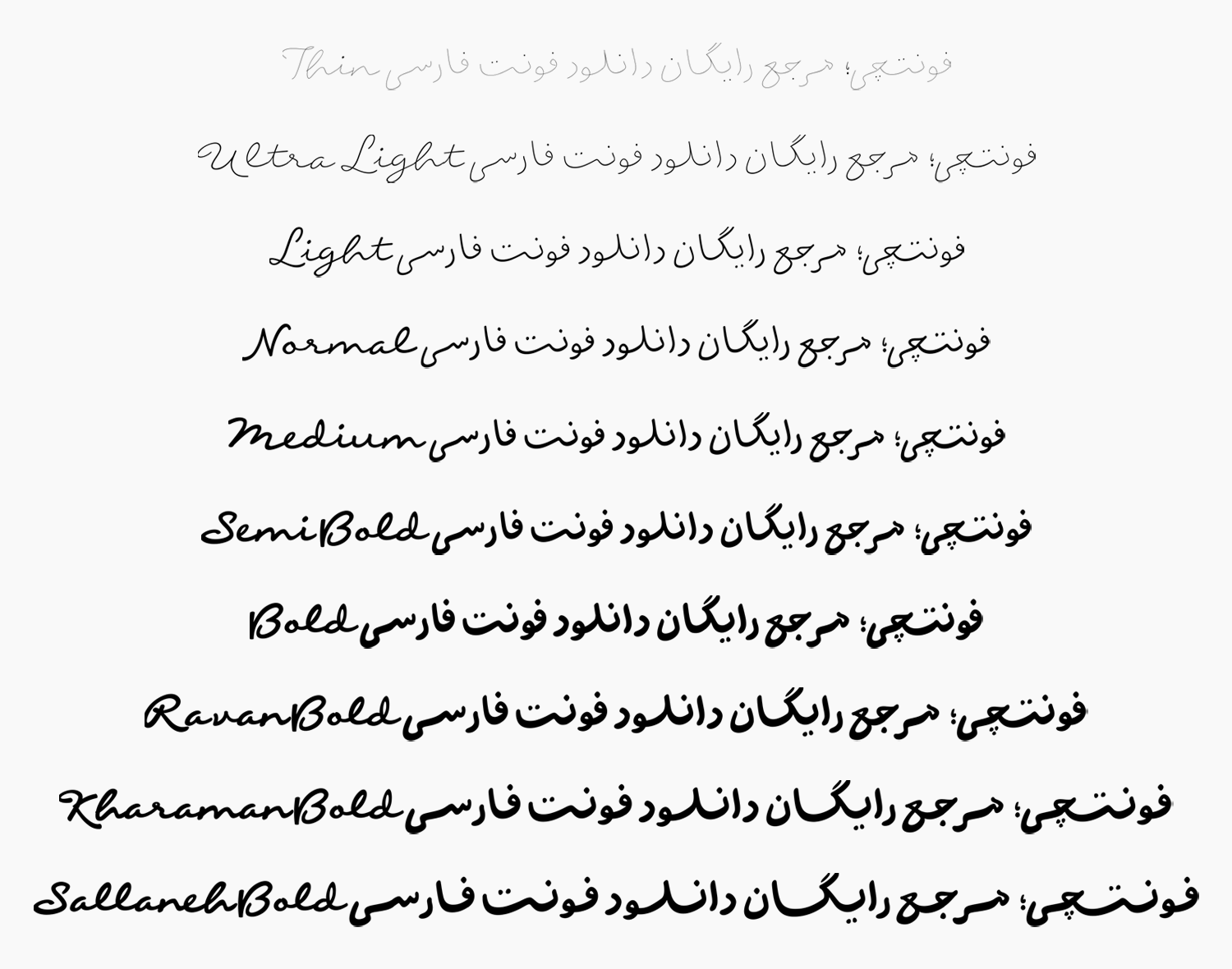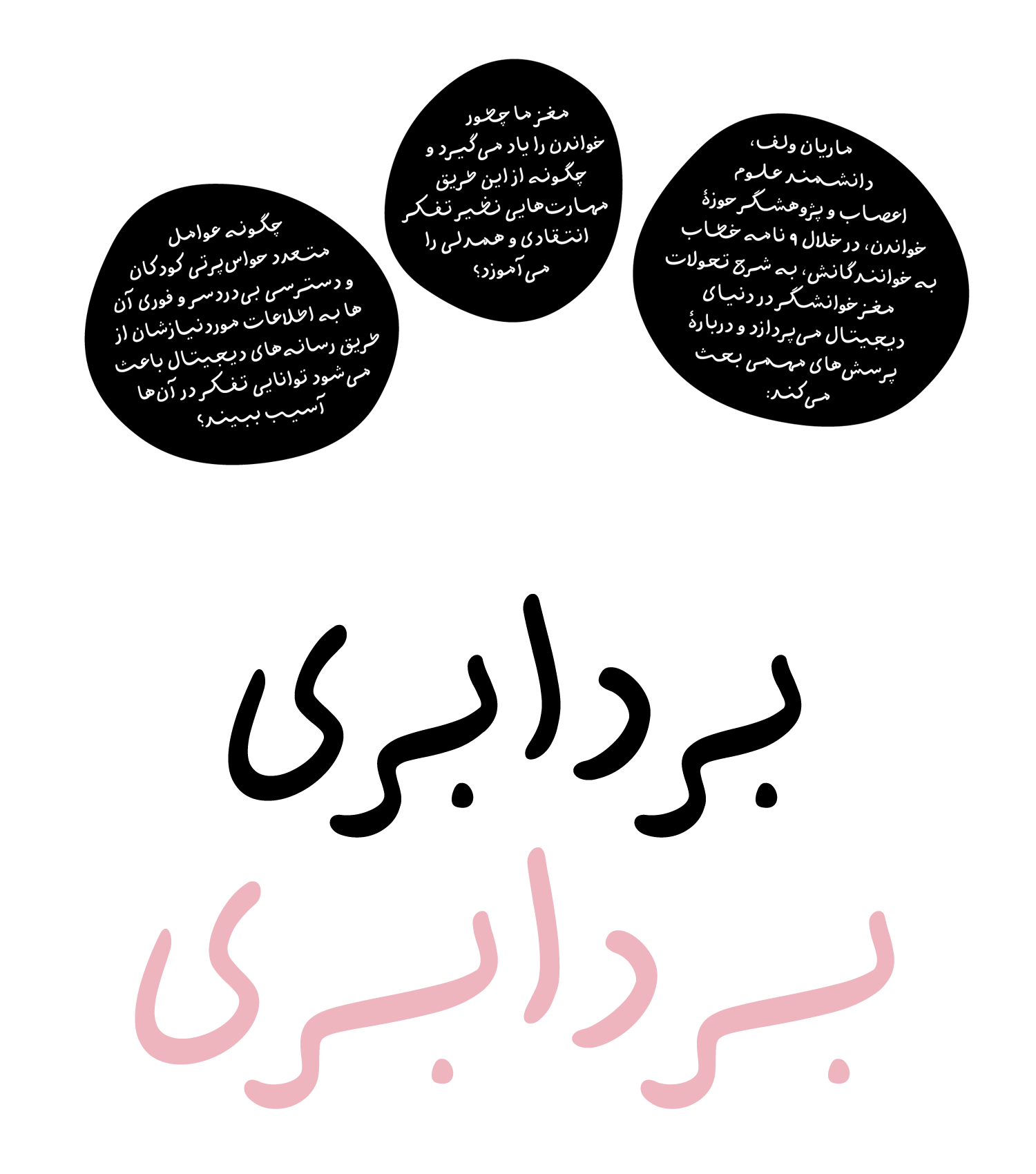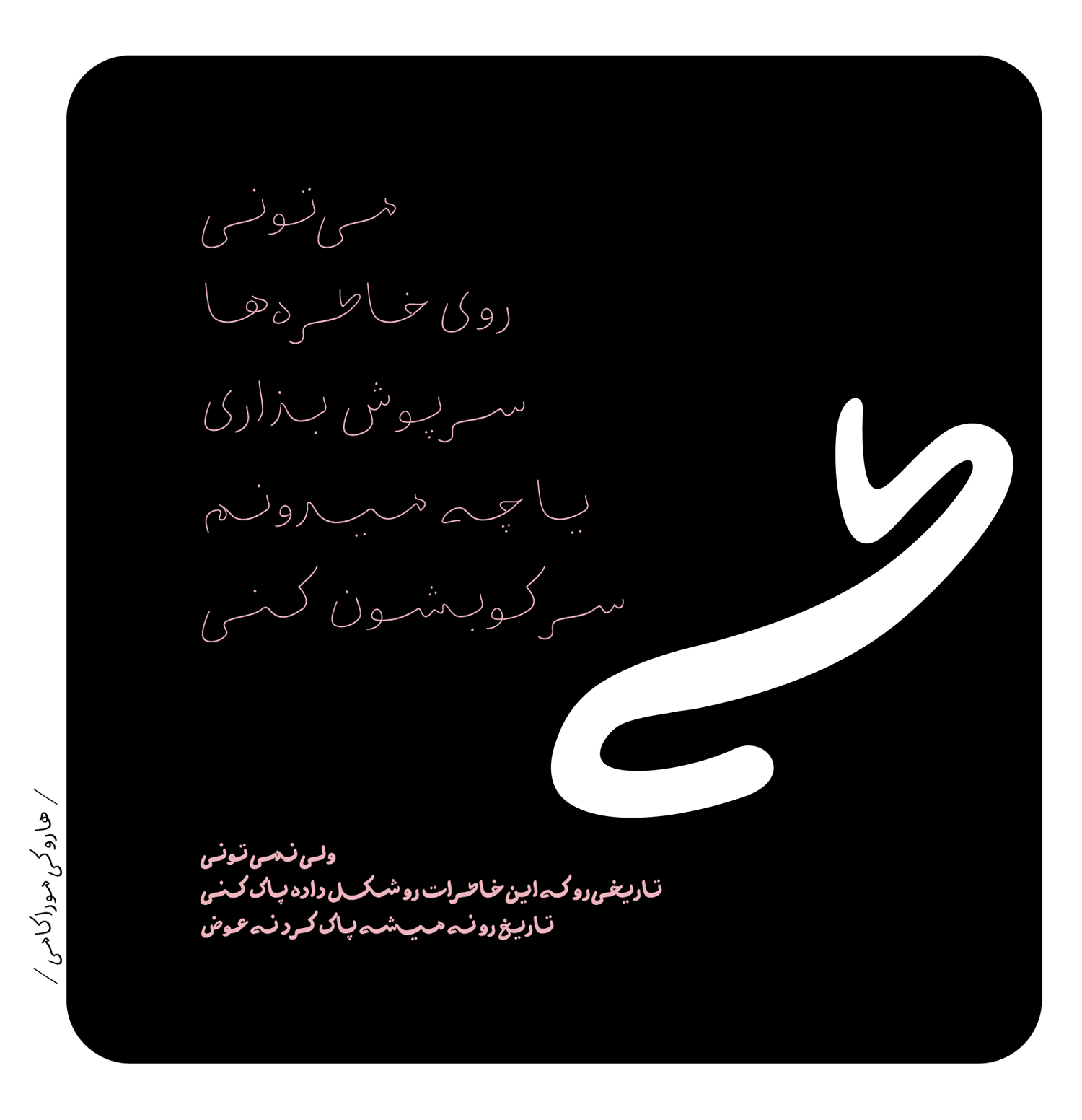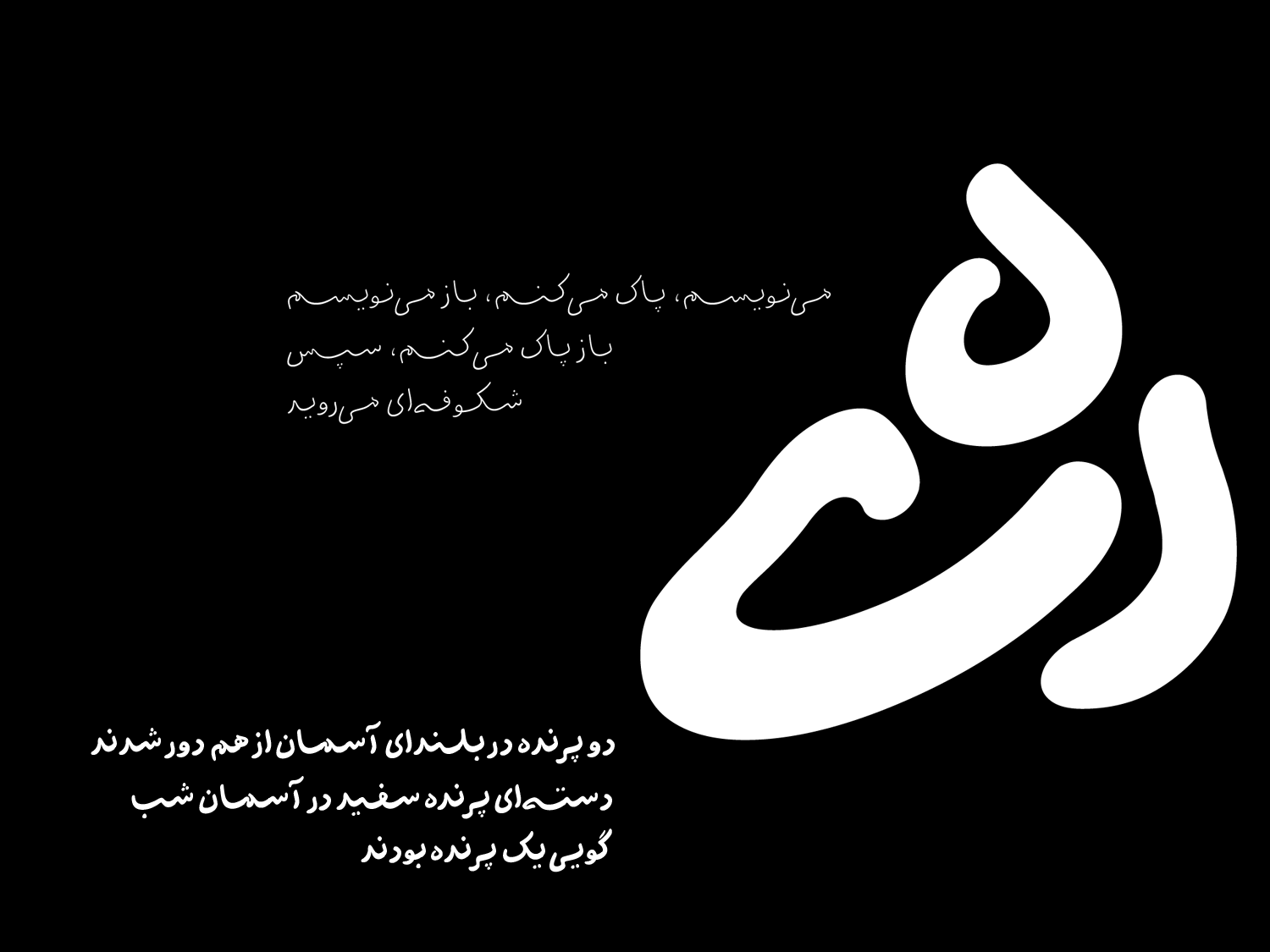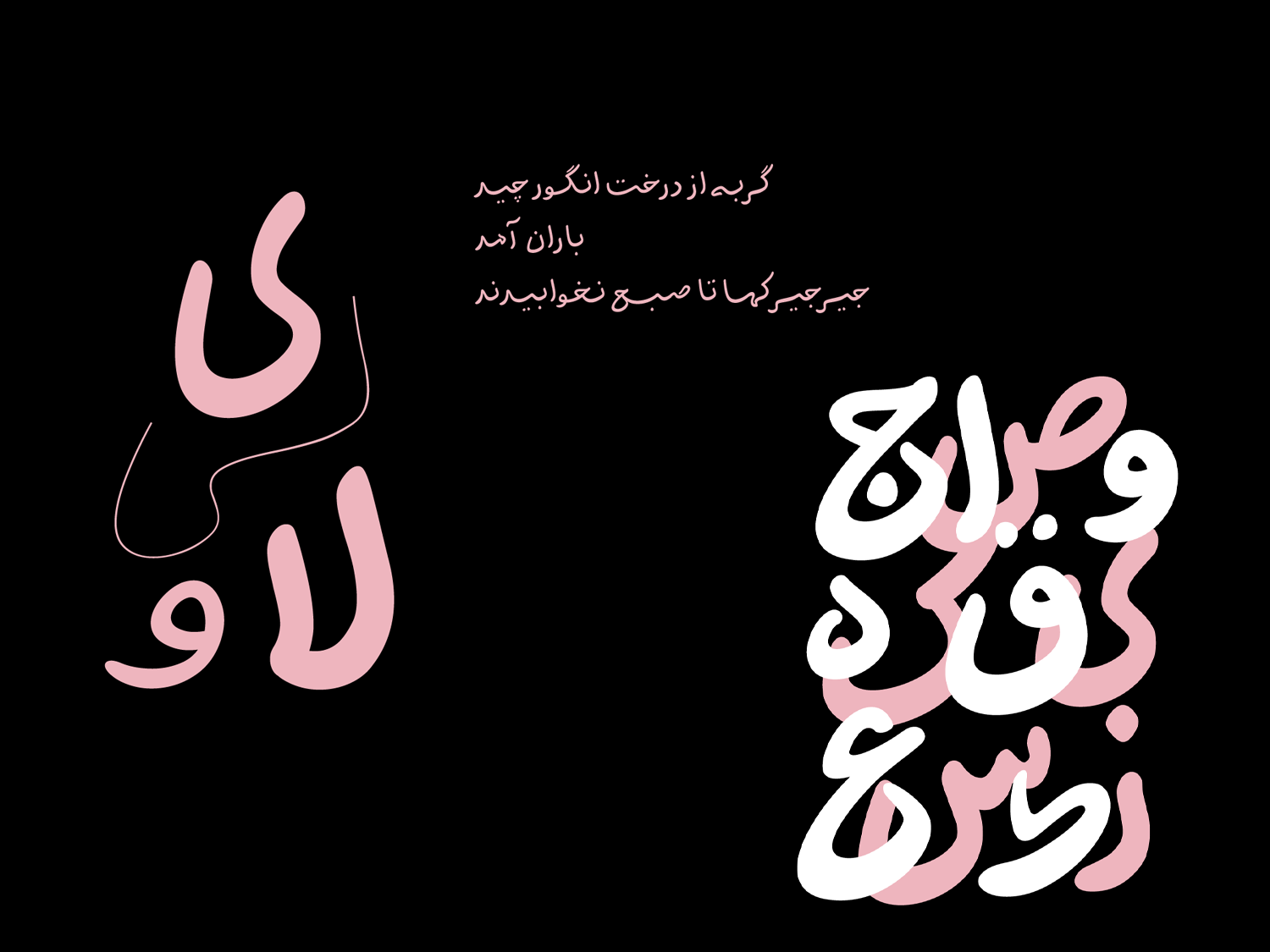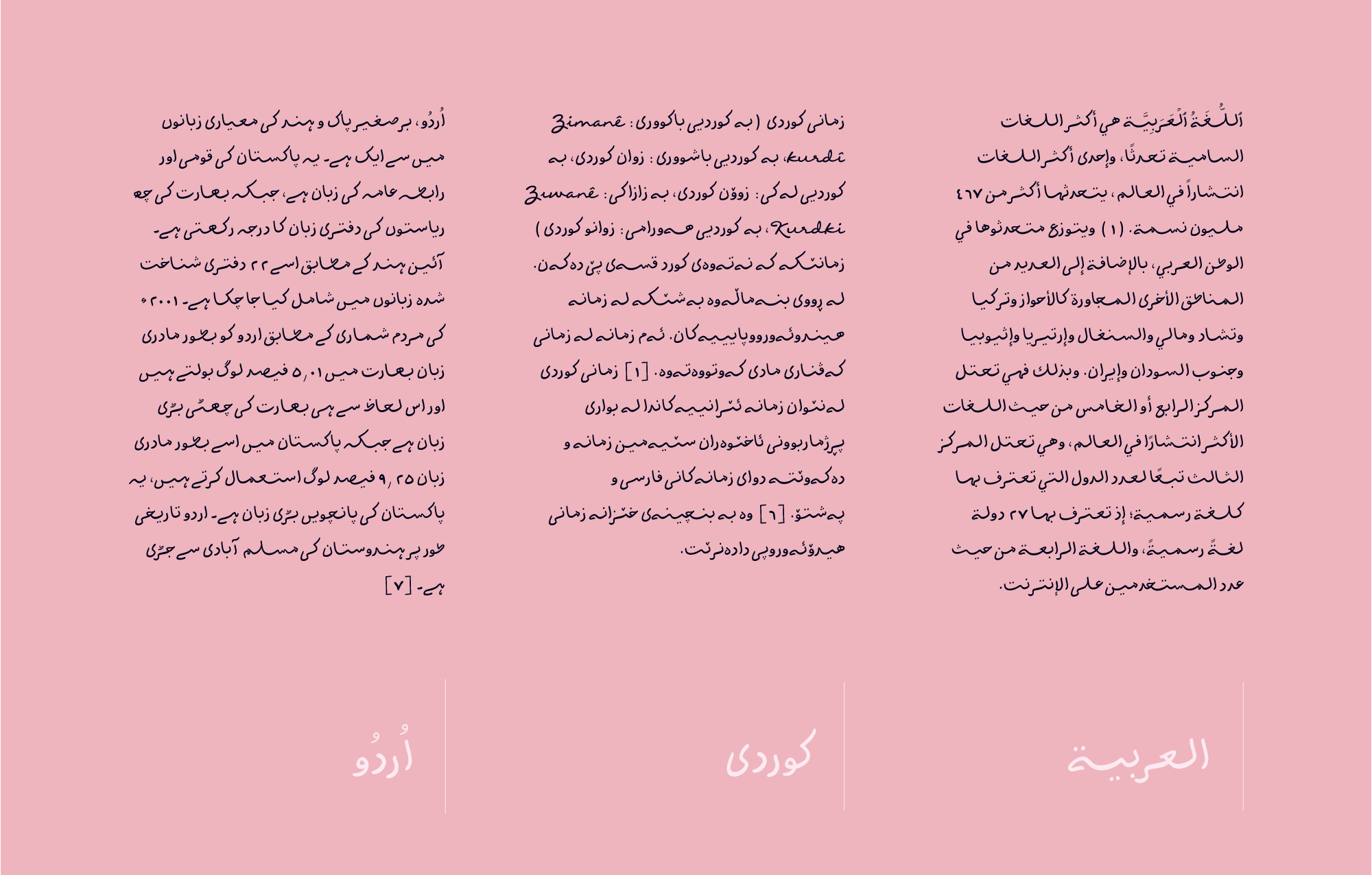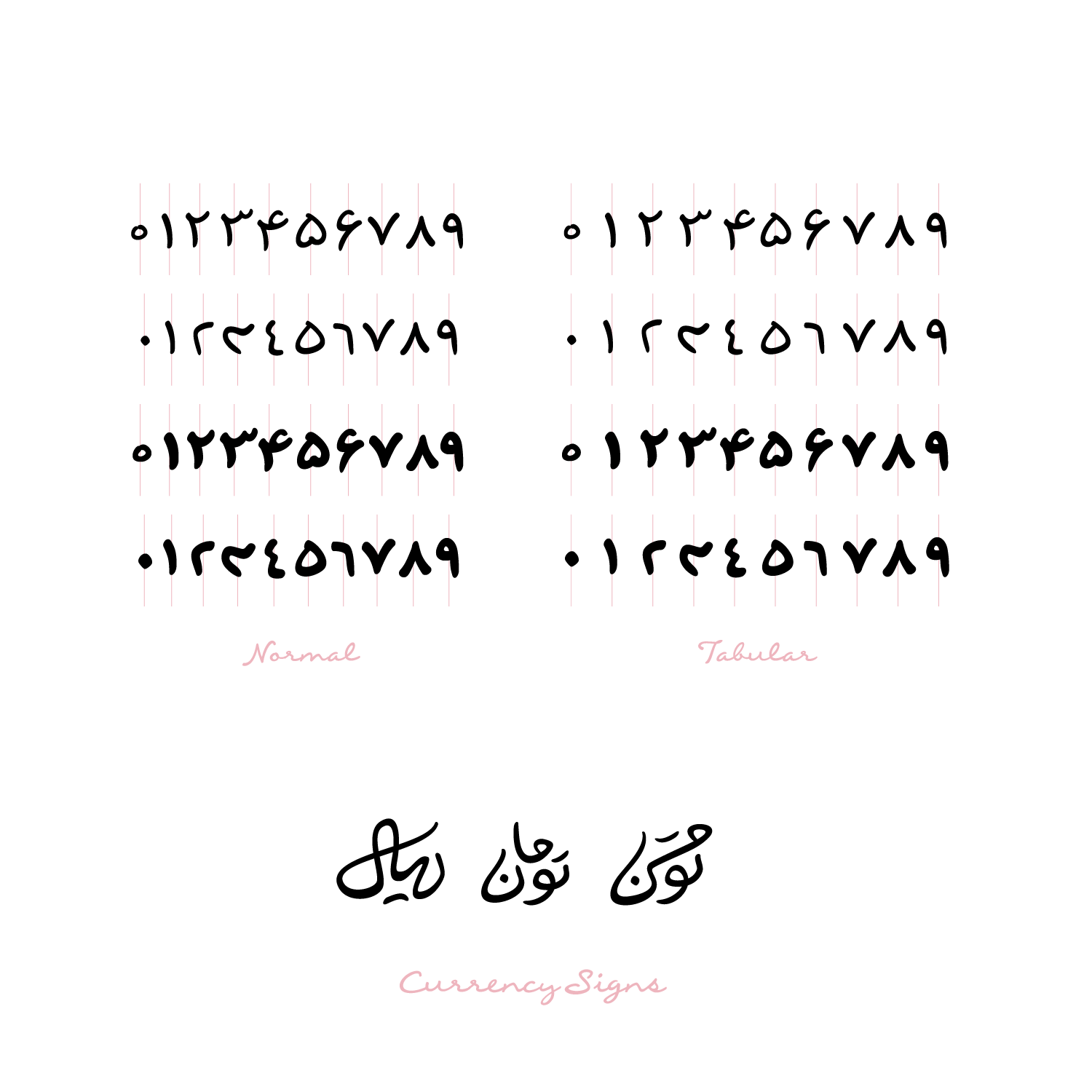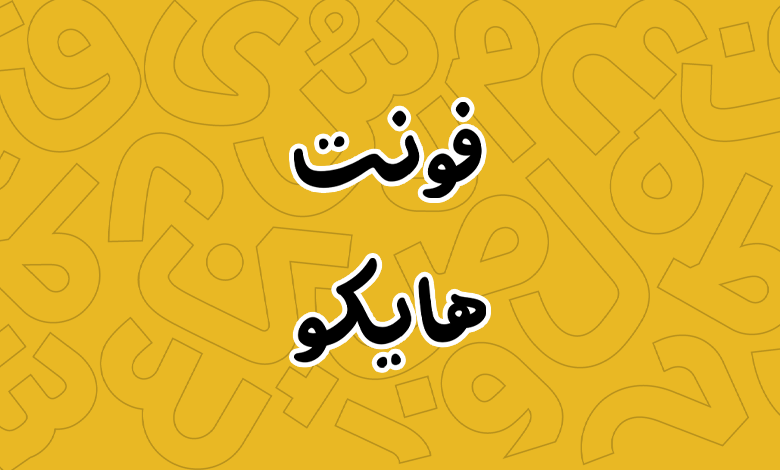
فونت هایکو (Haiku)
| طراح | علی پزشک |
فوت هایکو (به انگلیسی: Haiku) جدیدترین تایپفیس فارسی است که توسط علی پزشک، خلق شده است. این فونت دستنویس، با الهام از سنتهای خوشنویسی فارسی اما با رویکردی مدرن و الگوریتمیک، تلاش میکند تعادلی بین جریان طبیعی دستنویس و خوانایی دیجیتال برقرار کند.
هایکو بر پایه اتصال و همنشینی هوشمند حروف ساخته شده و از قالبهای سنتی حروفریزی فاصله گرفته است. کشیدگی حروف در آن به شیوهای نوآورانه مدیریت میشود. ابتدا کشیدگی به صورت اتوماتیک و الگوریتمیک بین حروف توزیع میشود تا ریتم و خوانایی ایجاد کند، سپس کاربر میتواند کشیدگی کلمات را در محور افقی کم یا زیاد کند.
فونت هایکو از ۷ وزن متنوع Thin تا Bold را پوشش میدهد. اما محدود به این نیست؛ در این فونت شاهد ۴ سبک سرعتی هستیم که در مجموع ۲۸ وزن مختلف را در اختیار قرار میدهد. چهار سبک (دوان، روان، خرامان، سلانه) که حس حرکت و روانی متفاوتی به حروف میدهند.
این ویژگیهای قلم، ساختار کشیدگی ماشینتایپی سنتی را غیرفعال کرده و اجازه میدهد متنها جریان طبیعیتری داشته باشند. شبیه به نوشتن با قلم واقعی بهنظر میرسند، اما ساختاری کنترل شدهتر به خود میگیرند.
فونت هایکو از زبانهای فارسی، عربی، کردی، اردو، و کاراکترهای لاتین انگلیسی پشتیبانی میکند. اعداد به دو شکل معمول و همعرض، همراه با نشانههای ریال و تومان طراحی شده است. اعراب و کاراکترهای خاص هر زبان نیز استاندارد خاص خود را دارد.